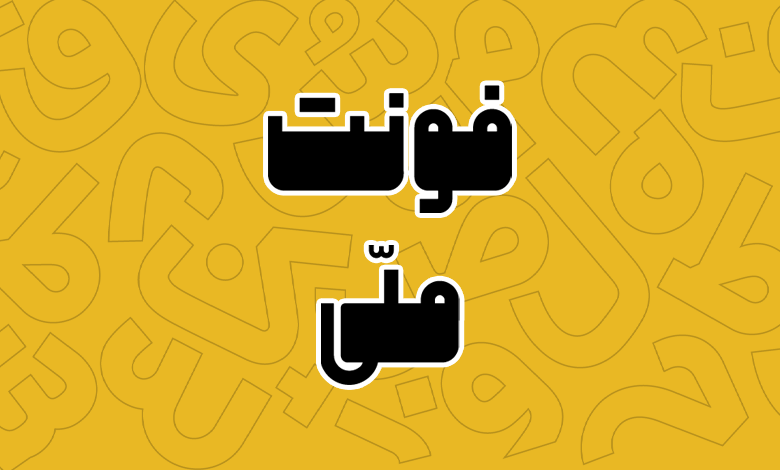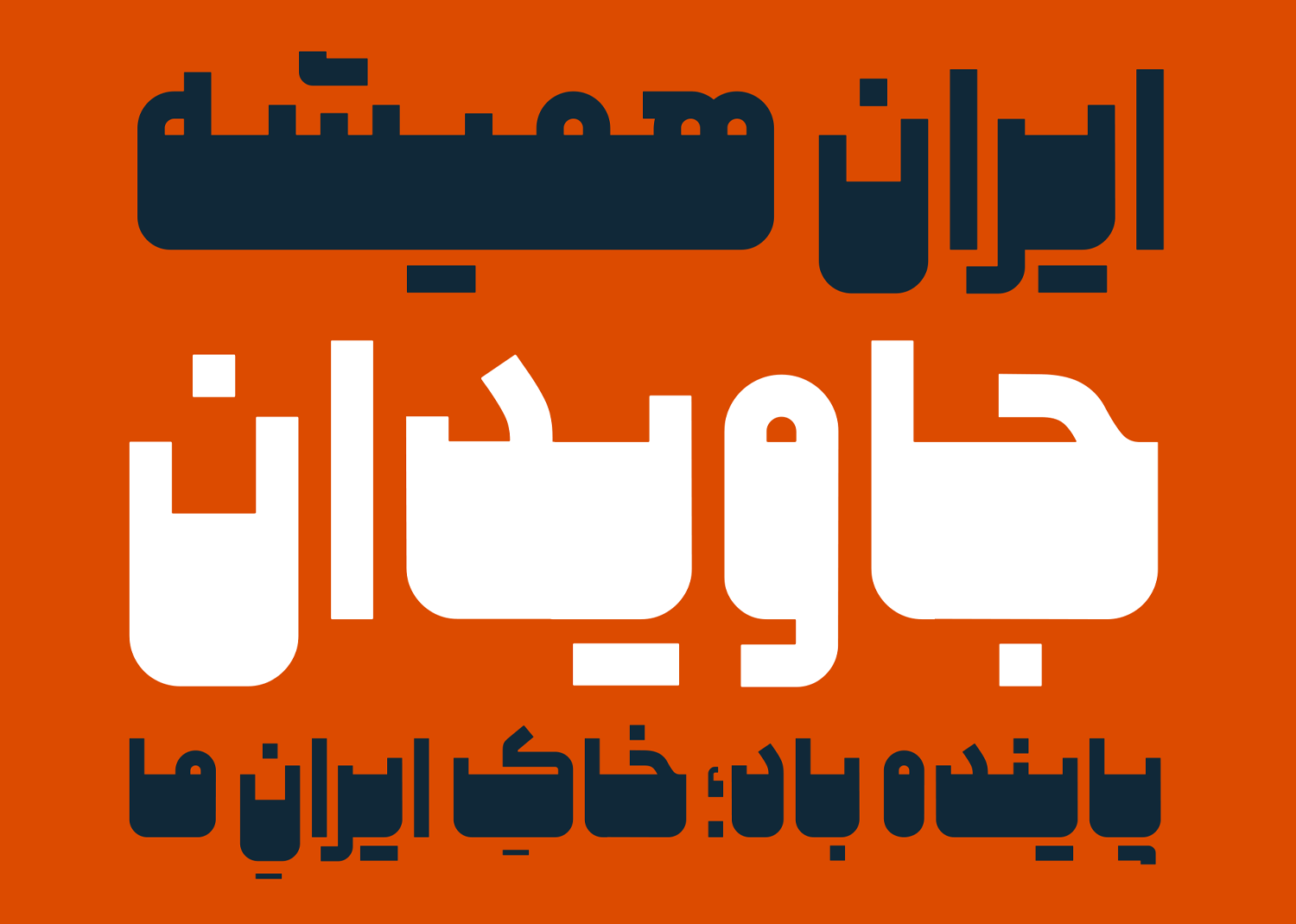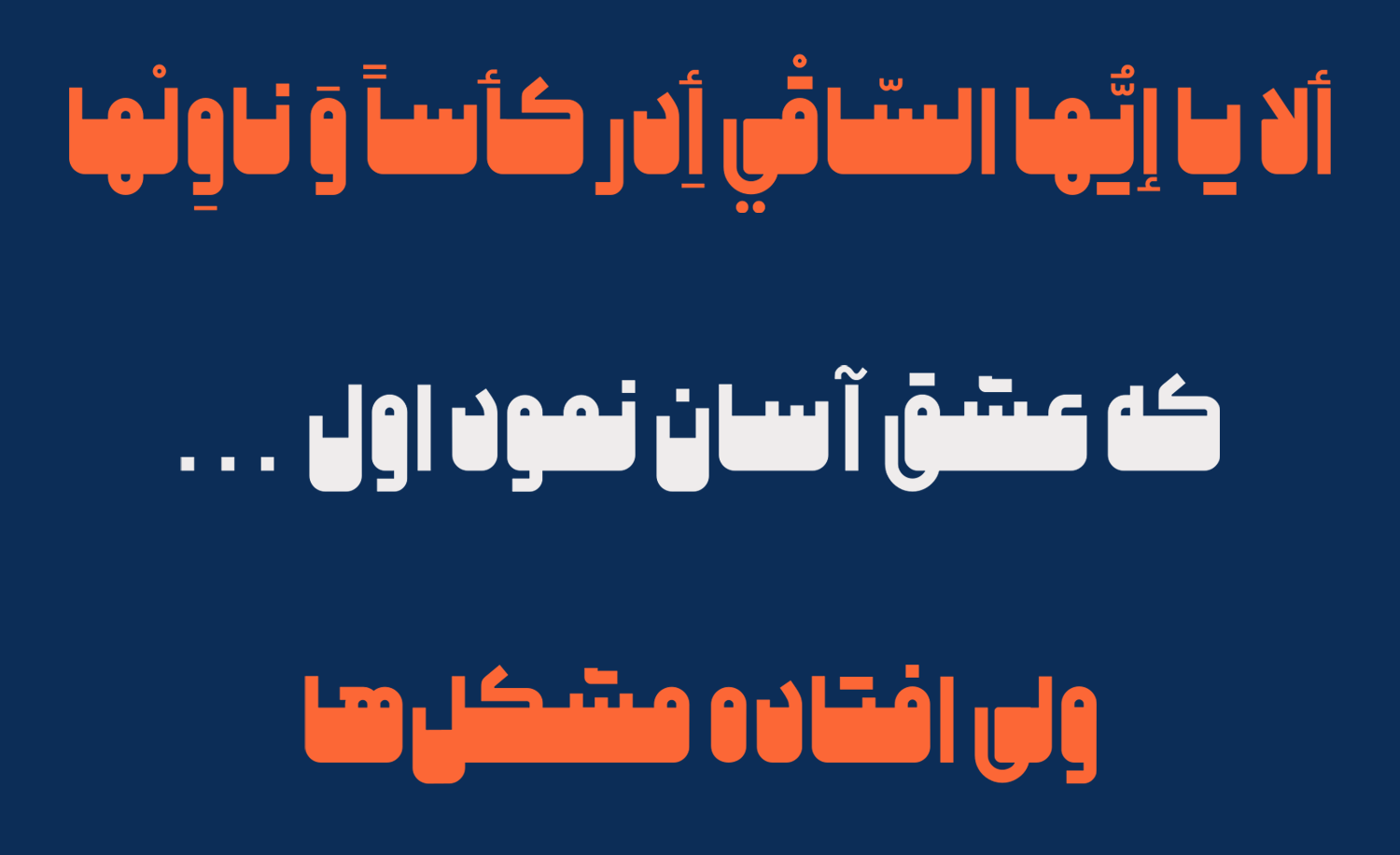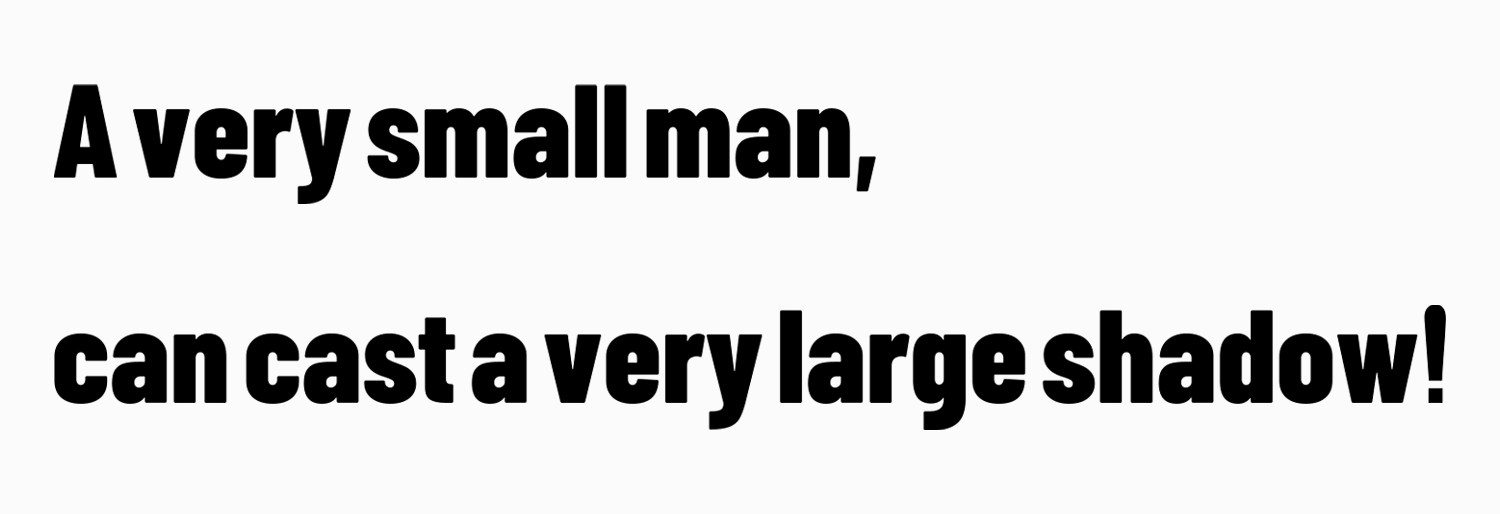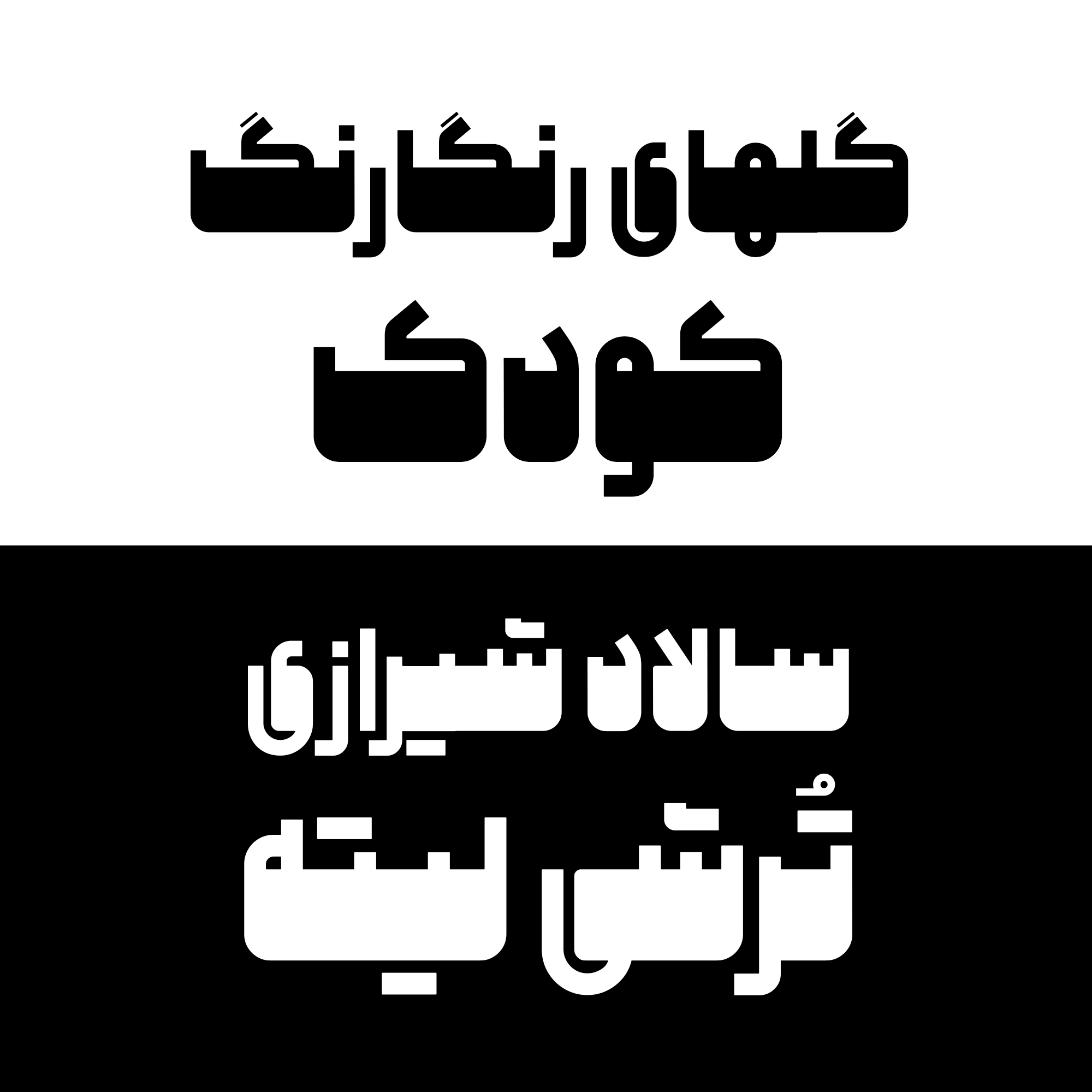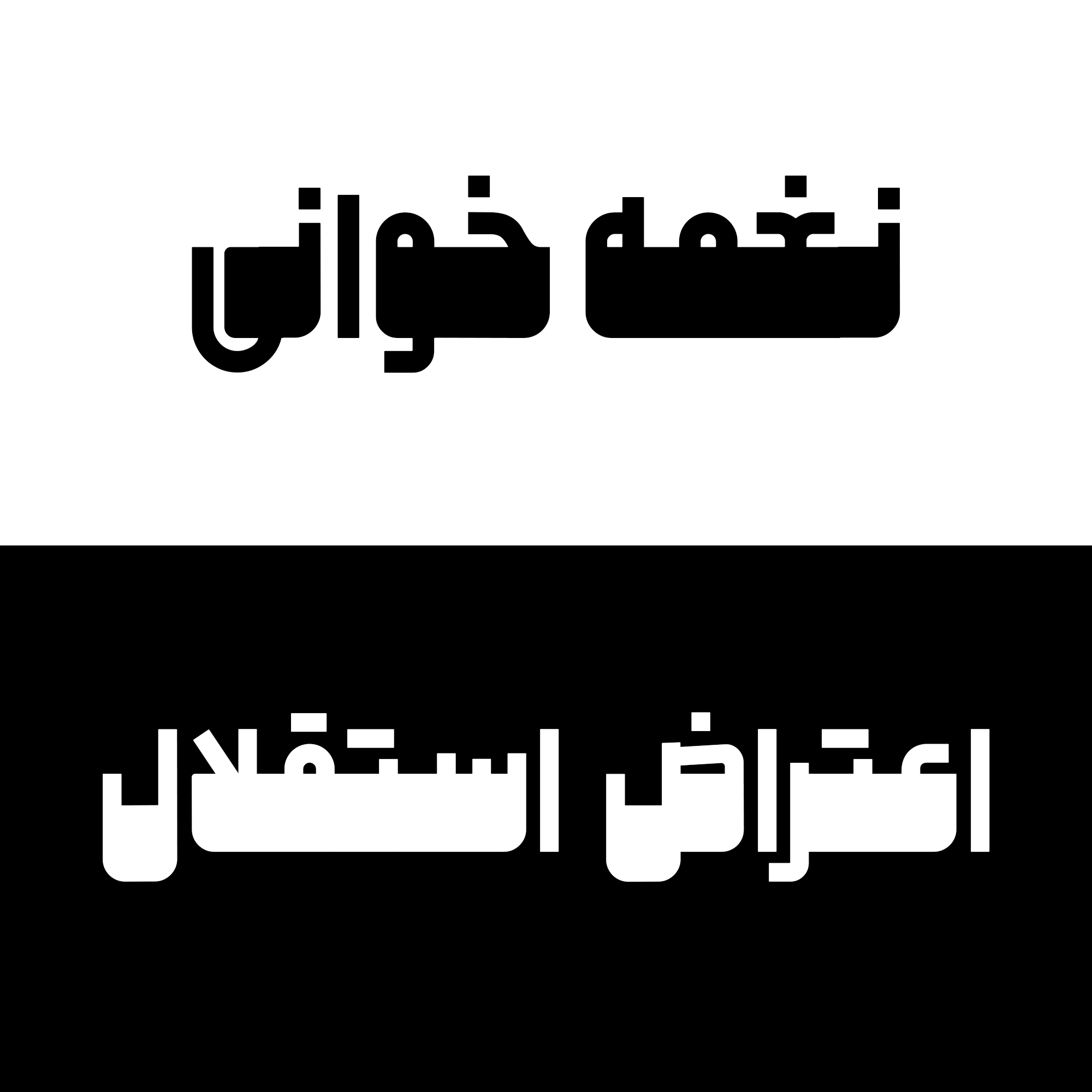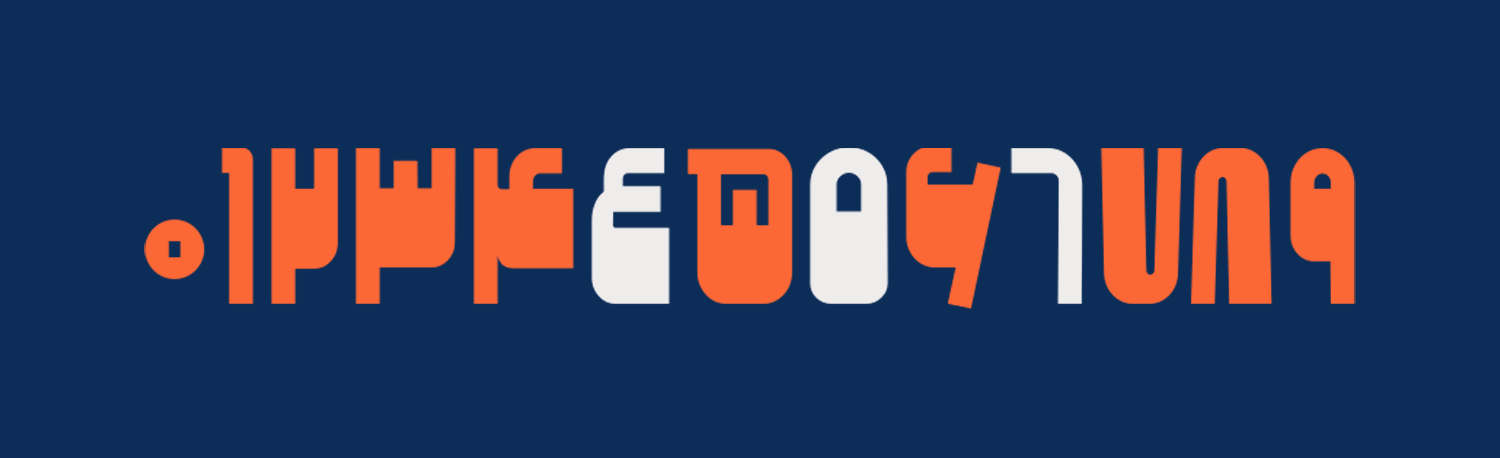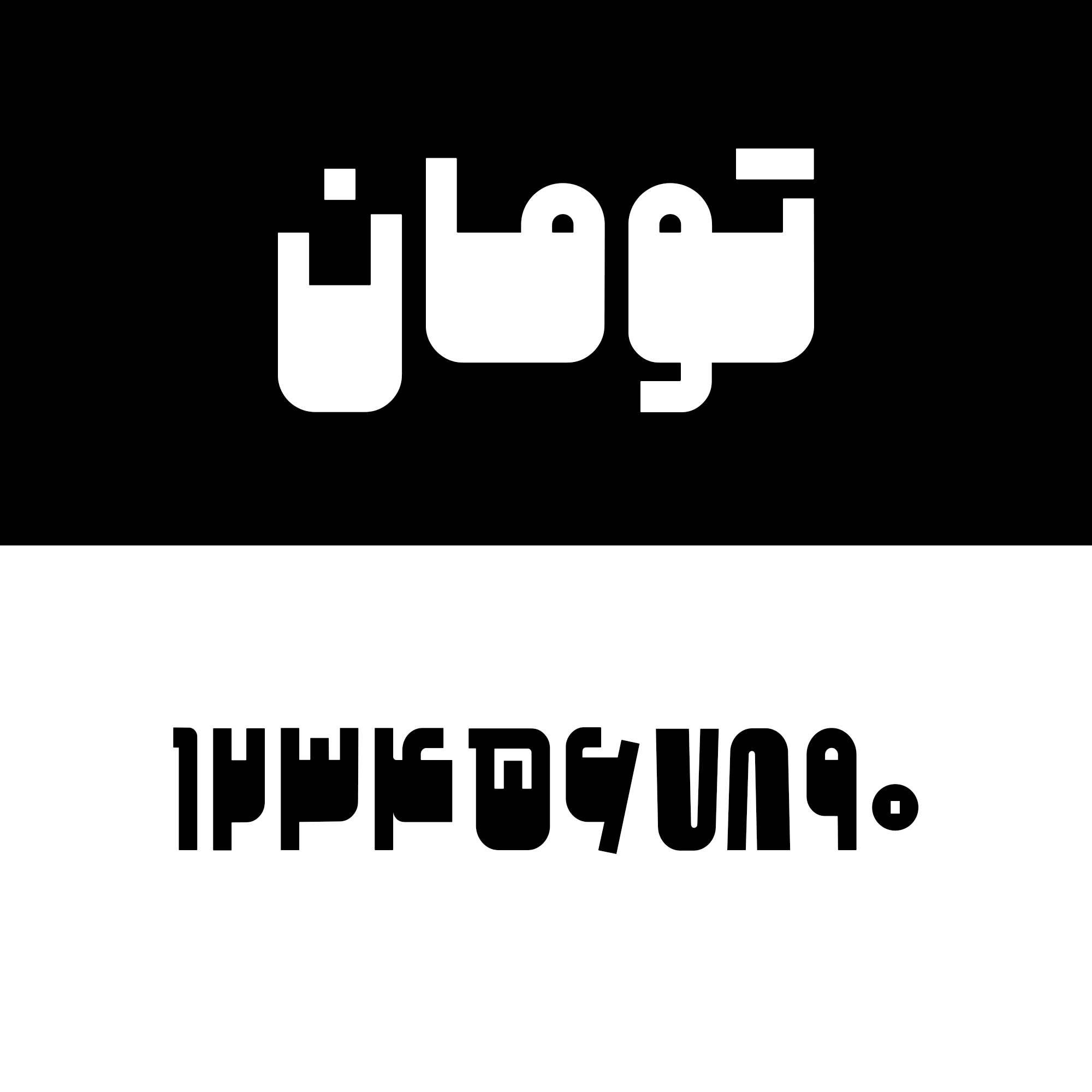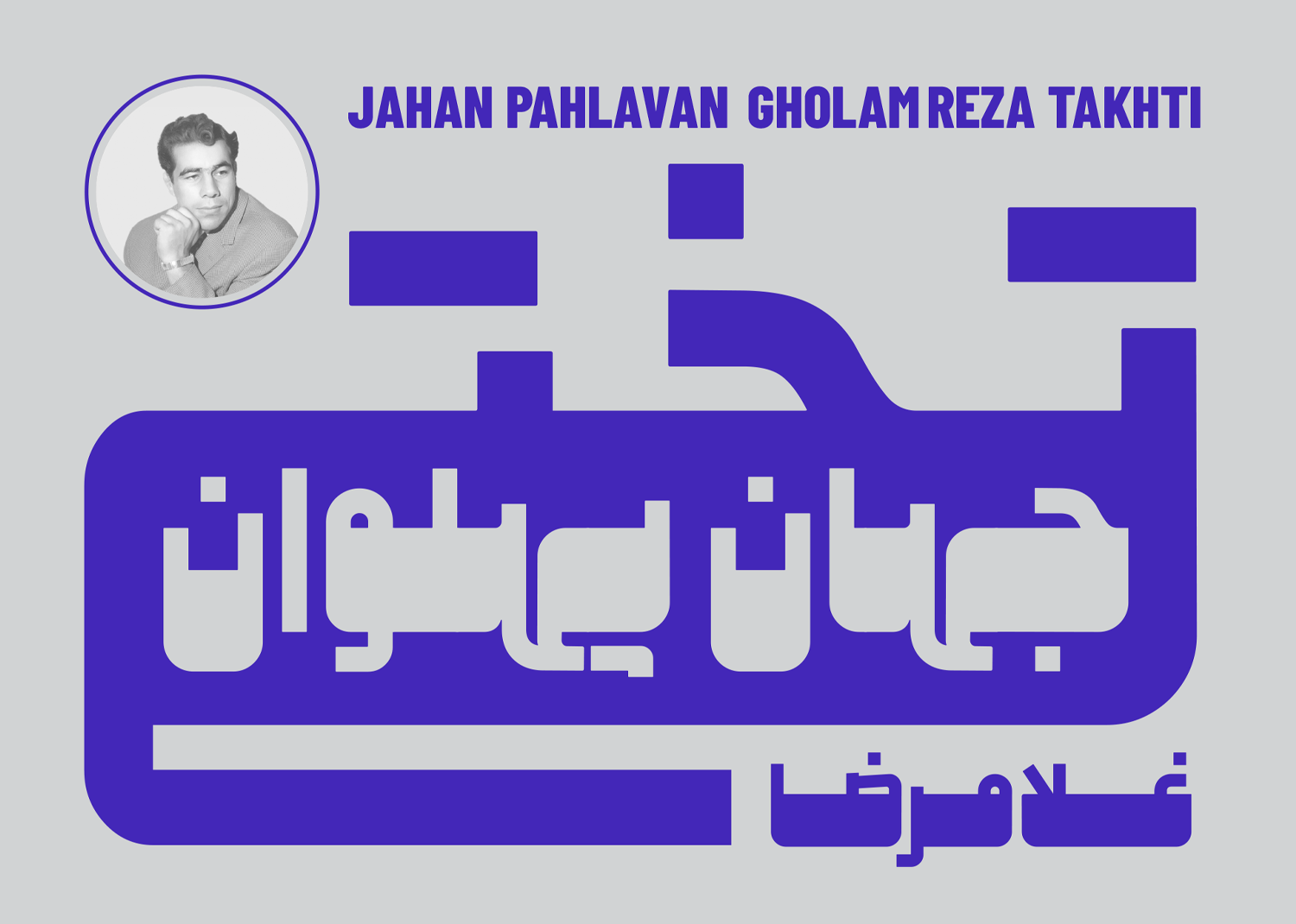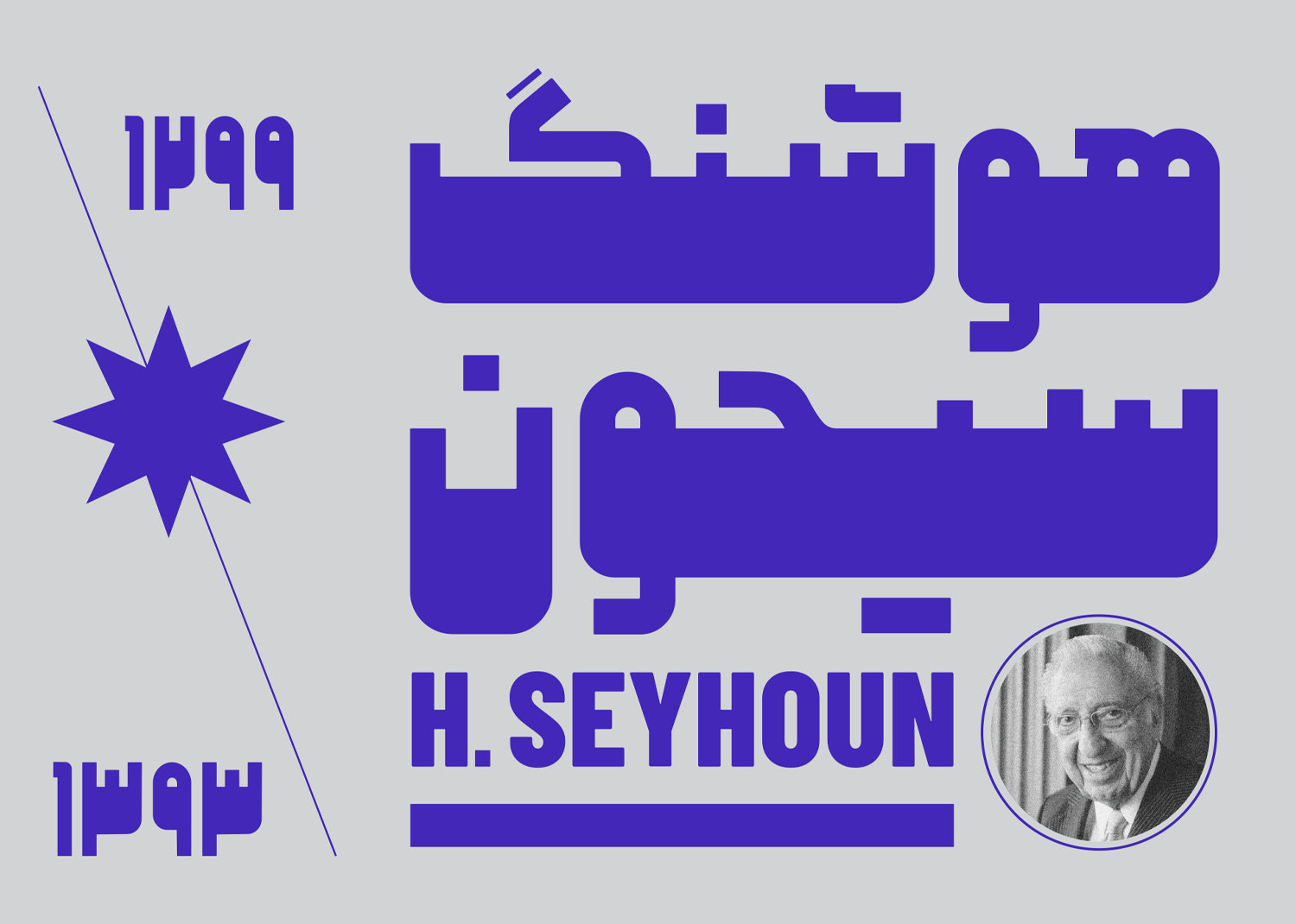
فونت ملی یا فونت ملّی (به انگلیسی: Melli) یکی دیگر از فونتهای جدید معرفی شده فارسی است که با ساختار خط کاملا هندسی طراحی شده است. این قلم در سرتاسر حروف برای تمامی زبانهای پشتیبانی شده از زوایای قائم، تند، خمیده و چاق در بخشهای افقی تشکیل شده است که گوشهها در تمامی بخشهای حروف، دندانهها و چشمیها به شکل کامل خمیده طراحی شدهاند.
اگر به دنبال دانلود فونت مناسبی برای استفاده در تبلیغات و عناوین هستید، فونت ملّی میتواند یکی از انتخابهای پیشروی شما باشد. چرا که سبک طراحی این قلم به گونهای است که ساختاری نوستالژیک متناسب با فونتهای قدیمی دهه ۴۰ و ۵۰ را دارد که بیشتر در سردرهای تابلو فروشگاهی دیده شدهاند.
فونت ملی دارای ساختاری به سبک طراحی هندسی است. این قلم مناسب عناوین طراحی شده و اگر قرار باشد نمونه فونت مشابه دیگری برای آن معرفی کنیم، فونت صداقت بیشترین نزدیکی و شباهت را به این فونت دارد.
در این قلم شاهد یک فونت سنگین با بدنهای کاملا قطور و چاق هستیم که یادآور فونتهای چاپی دهه ۴۰ و ۵۰ هستند. با اینکه فونتهای مختلفی با این سبک وجود دارد، اما فونت ملّی در مقایسه با آنها هندسه سادهتری داشته و همچنین کنتراست ضخامت حروف نیز نرمتر است.
سبک طراحی و وزن فونت ملی
فونت ملّی با سبکی طراحی شده که طراحی حروف کاملا منحنی نیست و به شکلی کاملا کنترل شده از خطوط و دایرهها شکل گرفته است. در حالی که خطوط افقی دارای ضخامت زیادی است، اما در مقابل خطوط قائم و مورب در خمیدگیها دارای وزن کمتری هستند.
ساقههای باریک و نازک در فونت ملی باعث شده تا کنتراست ضخامت حروف فشردهتر تایپ شده و از طرفی دیگر سنگینی این فونت بیشتر دیده شود. این فونت دارای ساختاری با یک وزن ایت که برای عناوین کوتاه با سایز بزرگ مناسب است که میتواند شامل طراحی جلد کتاب، طراحی پوستر، تبلیغات محیطی و وب فونت باشد.
پشتیبانی از چند زبان متنوع
فونت ملی به لطف رسم خط فارسی بودن، پشتیبانی کاملی را از سایر زبانهای خاورمیانه ای دارد که شامل عربی، اردو و کوردی میشود. در تمامی این زبانها حروف و کاراکترهایی که مشترک هستند از همان سبک طراحی برخوردار هستند.
در مقابل سایر زبانهایی که دارای حروف و ترکیبات متفاوت هستند، گلیف و لیگچرهای اختصاصی خود را دارند. به عنوان مثال حروف «ك، ي، ة، ؤ، ئ» در زبان عربی یا حروف «ﮧ، ﮩ، ے» در زبان اردو که متفاوت به حروف فارسی هستند گلیف اختصاصی خود را دارا میباشند.
اعراب و کاراکترهای دیگر نظیر «سکون، تنوینها، تشدید، همزه» که در بالا یا پایین حروف نیز قرار میگیرند در تمامی زبانها به شکل درستی پشتیبانی شدهاند. اعراب در حروف عربی طوری است که هم نشینی درستی با هر یک از حروف دارند و قرارگیری آنها در کنار تشدید یا همزه باعث بههم ریختگی یا چسبیدن به حروف قبل یا بعد نمیگردد.
با اینکه فونت ملی از زبان انگلیسی هم پشتیبانی میکند، اما ساختار طراحی آن در این زبان شکل هندسی نسخه فارسی را که شامل دو نوع کنتراست ضخیم و نازک است را نداشته و از یک فونت پیشفرض با وزن سیاه برای آن استفاده شده است تا لزوما احتیاجی به تغییر فونت برای حروف لاتین نداشته باشید.
دارای ترکیبات و حروف جایگزین متنوع
ویژگی دیگر فونت ملی پشتیبانی از حروف جایگزین و ترکیبات است که امکان تایپ متفاوت را برای کلمات خواهد داد. در فونتهای مناسب تبلیغات این موضوع از اهمیت بالایی برخوردار است تا بتوانید در طراحی کاور و پوسترهای خود نگاه مخاطب را بدزدید.
همانطور که در تصویر زیر مشاهده میکنید، حروف «ک» و «گ» با توجه به اینکه در ابتدا، میانه یا انتهای کلمات باشند، قابلیت تغییر به حالت کشیده با مقدار ۲ درجه را دارند. همچنین حروف «ه وسط» و « ﮧ، ﮩ میانی و آخر به سبک فونت نستعلیق» دارای حالتهای جایگزین هستند.
حرف «ی» میتواند بصورت معکوس (ے) تغییر یابد و میزان کشیدگی ۲ درجه نیز روی آن اعمال گردد. به همین ترتیب حروف «س» و «ش» هم میتواند به حالت کشیده تغییر کند.
برای حروفی مانند «ن، س، ش، ص، ض، ق، ل» علاوه بر اینکه ساختار جایگزین وجود دارد، میتوانید کاسه حروف را به حالت گرد تغییر دهید که شامل حروف تکی یا استفاده در ترکیبات میشود.
این موارد محدود به اینها نبوده و متناسب با فایل راهنما موجود در بسته دانلود فونت ملی میتوانید با سایر حروف جایگزین و ترکیبات آلترنیتیو آشنا شوید.
پشتیبانی حرفه ای اعداد با گلیف تومان و ریال
از دیگر قابلیتهای فونت فارسی ملی میتوان به پشتیبانی حرفهای اعداد چه برای زبانهای خاورمیانهای مبتنی بر رسم خط فارسی و چه زبانهای لاتین اشاره کرد. در این فونت گلیفهای اعداد بر اساس ساختار بین المللی هر زبان طراحی و اجرا شده است.
به عنوان نمونه همانطور که در تصویر زیر مشاهده میکنید، اعداد عربی «٤٥٦» که شکل متفاوتتری نسبت به اعداد فارسی «۴۵۶» دارند، گلیف استاندارد خود را دارا میباشند. زبان صفحه کلید روی هر یک از زبانهای فارسی یا غیر فارسی که باشد اعداد متناسب با همان زبان تایپ خواهند شد.
افزون بر این امکان تغییر اعداد را با استفاده از تنظیمات OpenType در نرمافزارهای گرافیکی همچون فتوشاپ و ایلاستریتور خواهید داشت. در زبانهای لاتین نیز همان سبک طراحی زاویهدار با خطوط قائم خاص این فونت در نظر گرفته شده است.